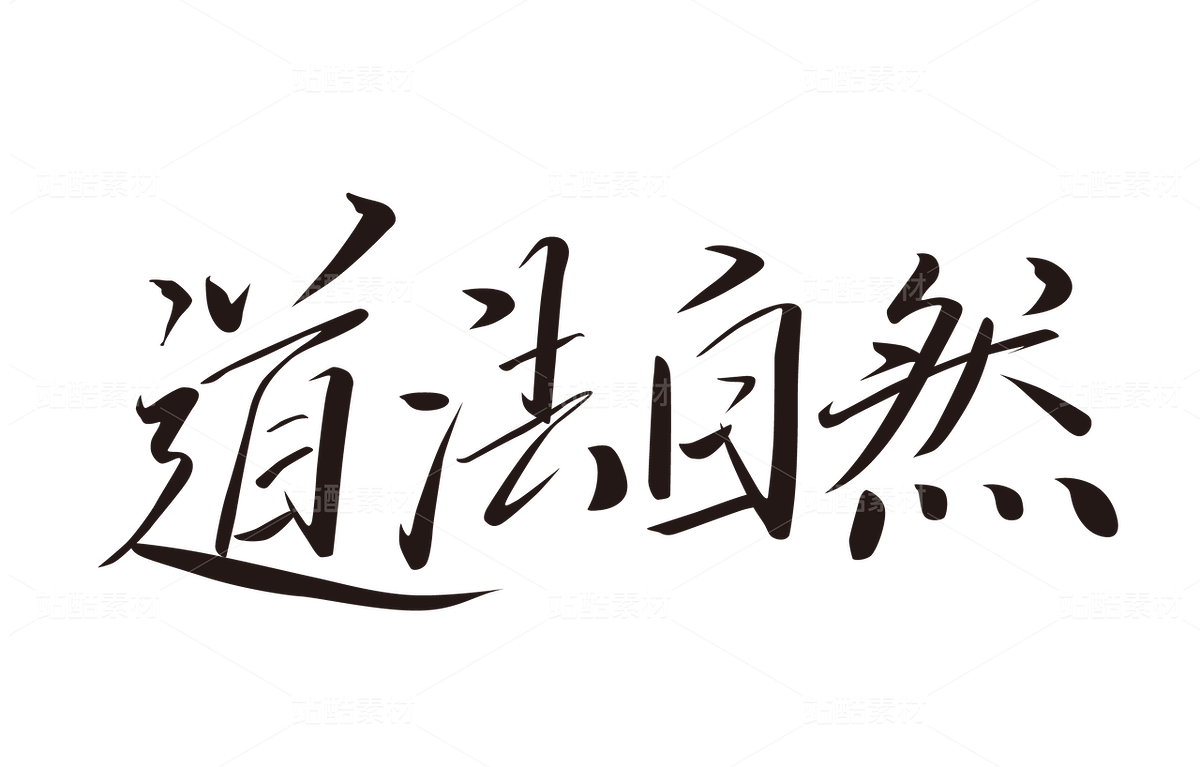
笔韵之美
这组 “道法自然” 手写字体,笔画灵动飘逸,似有清风拂过。起笔与收笔处,或轻盈如蝶翼点水,或厚重若苍岩坠地,尽显书法韵味。“道” 字首笔如奇峰突起,似在引领观者探寻深邃哲理;“法” 字笔画婉转流畅,恰如自然之律的灵动流转;“自” 字笔画简洁却蕴含张力,似一方天地自成;“然” 字四点如灵动星火,赋予字体活泼生气,又似自然中的点滴妙趣。
结构之妙
在结构布局上,四个字大小、疏密巧妙搭配。“道” 字开阔舒展,如大道坦途,包容万象;“法” 字紧凑而不失灵动,于规矩中见变化;“自” 字方正稳健,似自然之根基沉稳;“然” 字略宽,与其他三字相互呼应,整体呈现出一种和谐又富有变化的平衡感,恰似自然万物既独立又共生的状态 。
意境之合
字体风格与 “道法自然” 的内涵完美契合。洒脱而不失庄重的笔触,传递出对自然规律的尊崇与顺应。其自由随性的笔画形态,仿佛让人看到自然中云卷云舒、花开花落的自在之态,将道家崇尚自然、无为而治的深邃思想,以直观且优美的视觉形式呈现,给人以精神上的启迪与美的享受 。
这组 “道法自然” 手写字体,笔画灵动飘逸,似有清风拂过。起笔与收笔处,或轻盈如蝶翼点水,或厚重若苍岩坠地,尽显书法韵味。“道” 字首笔如奇峰突起,似在引领观者探寻深邃哲理;“法” 字笔画婉转流畅,恰如自然之律的灵动流转;“自” 字笔画简洁却蕴含张力,似一方天地自成;“然” 字四点如灵动星火,赋予字体活泼生气,又似自然中的点滴妙趣。
结构之妙
在结构布局上,四个字大小、疏密巧妙搭配。“道” 字开阔舒展,如大道坦途,包容万象;“法” 字紧凑而不失灵动,于规矩中见变化;“自” 字方正稳健,似自然之根基沉稳;“然” 字略宽,与其他三字相互呼应,整体呈现出一种和谐又富有变化的平衡感,恰似自然万物既独立又共生的状态 。
意境之合
字体风格与 “道法自然” 的内涵完美契合。洒脱而不失庄重的笔触,传递出对自然规律的尊崇与顺应。其自由随性的笔画形态,仿佛让人看到自然中云卷云舒、花开花落的自在之态,将道家崇尚自然、无为而治的深邃思想,以直观且优美的视觉形式呈现,给人以精神上的启迪与美的享受 。